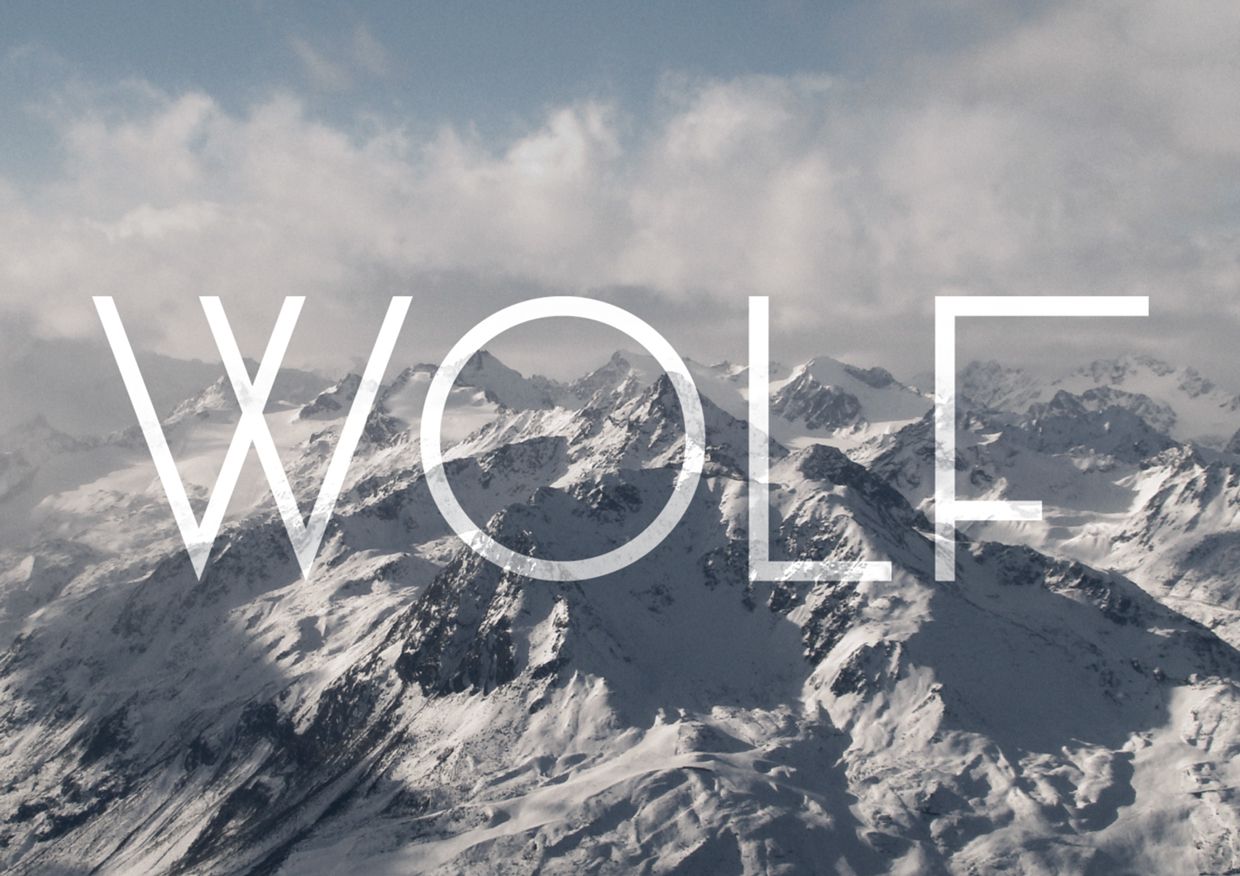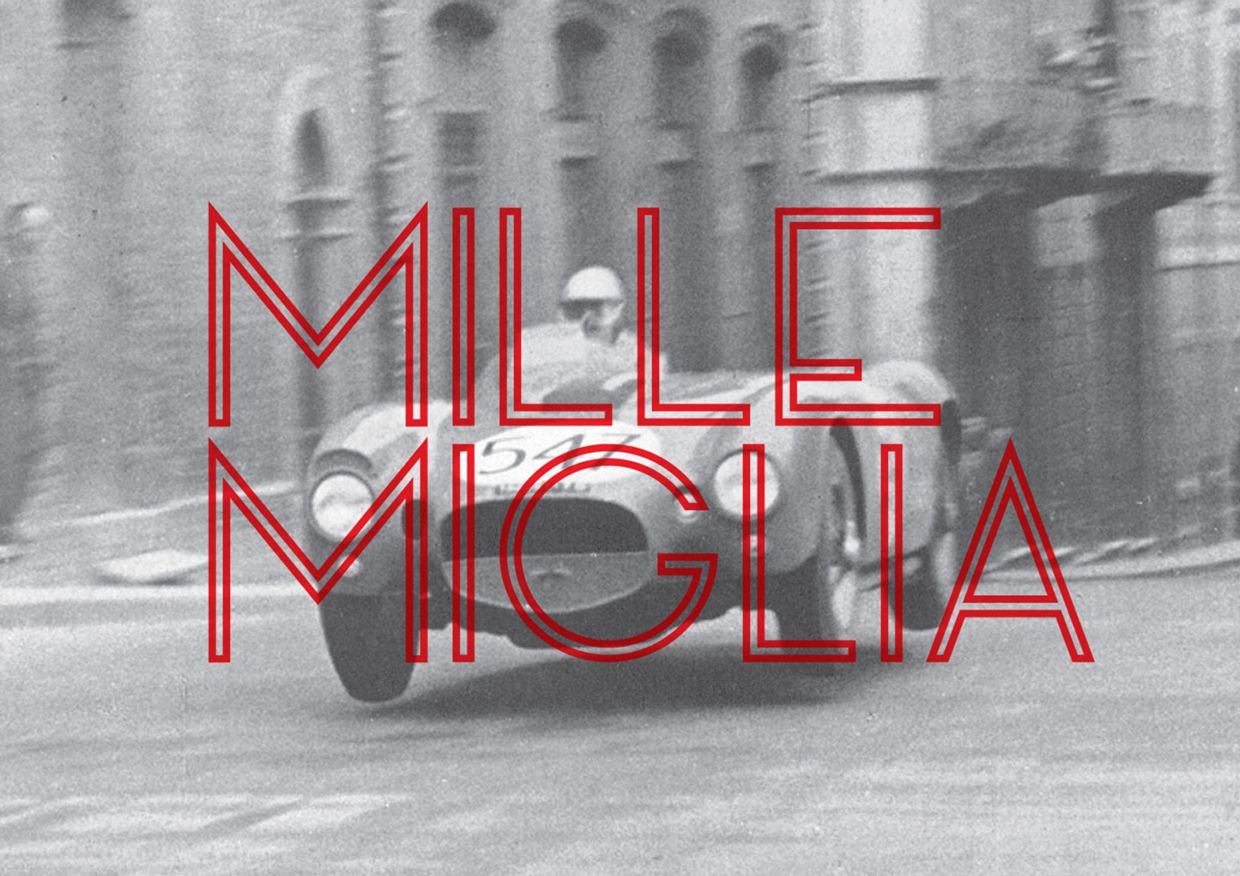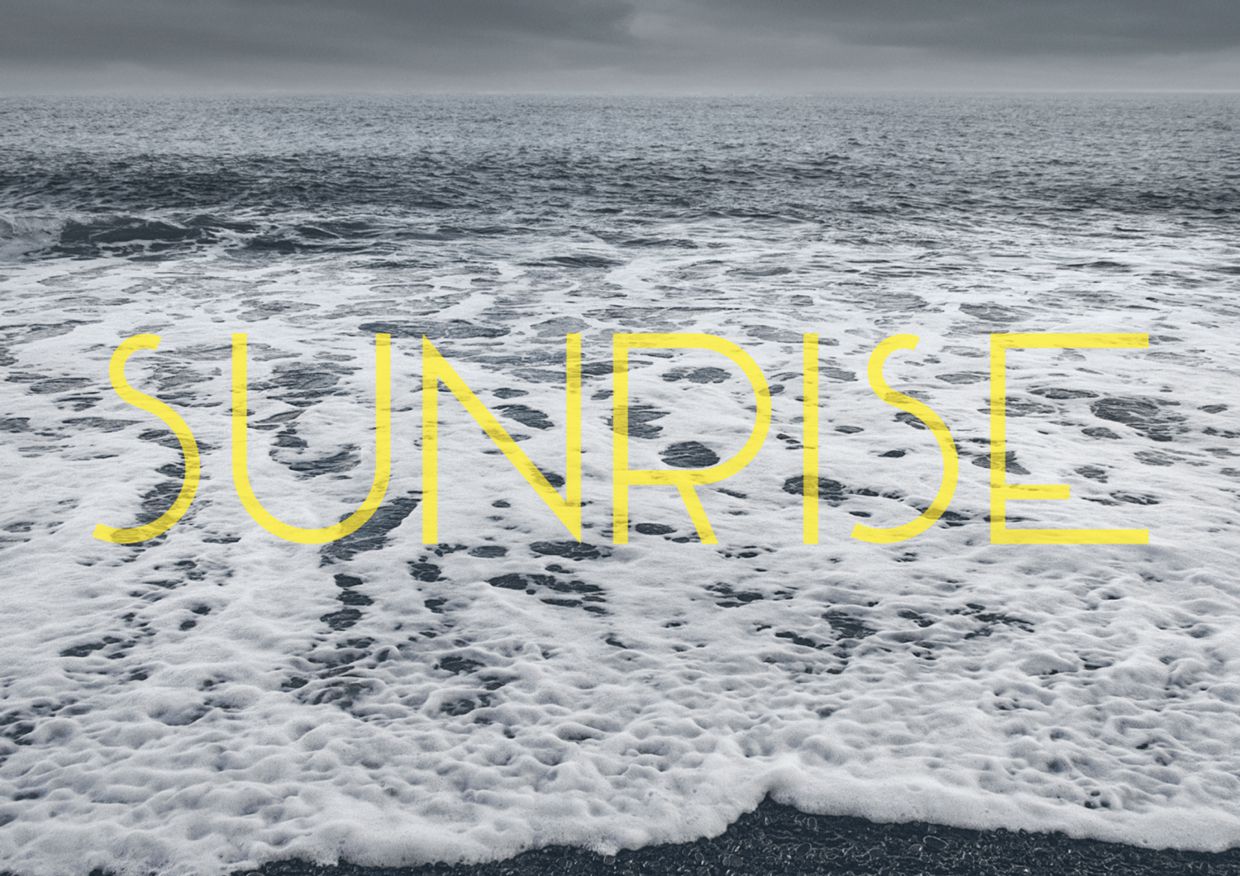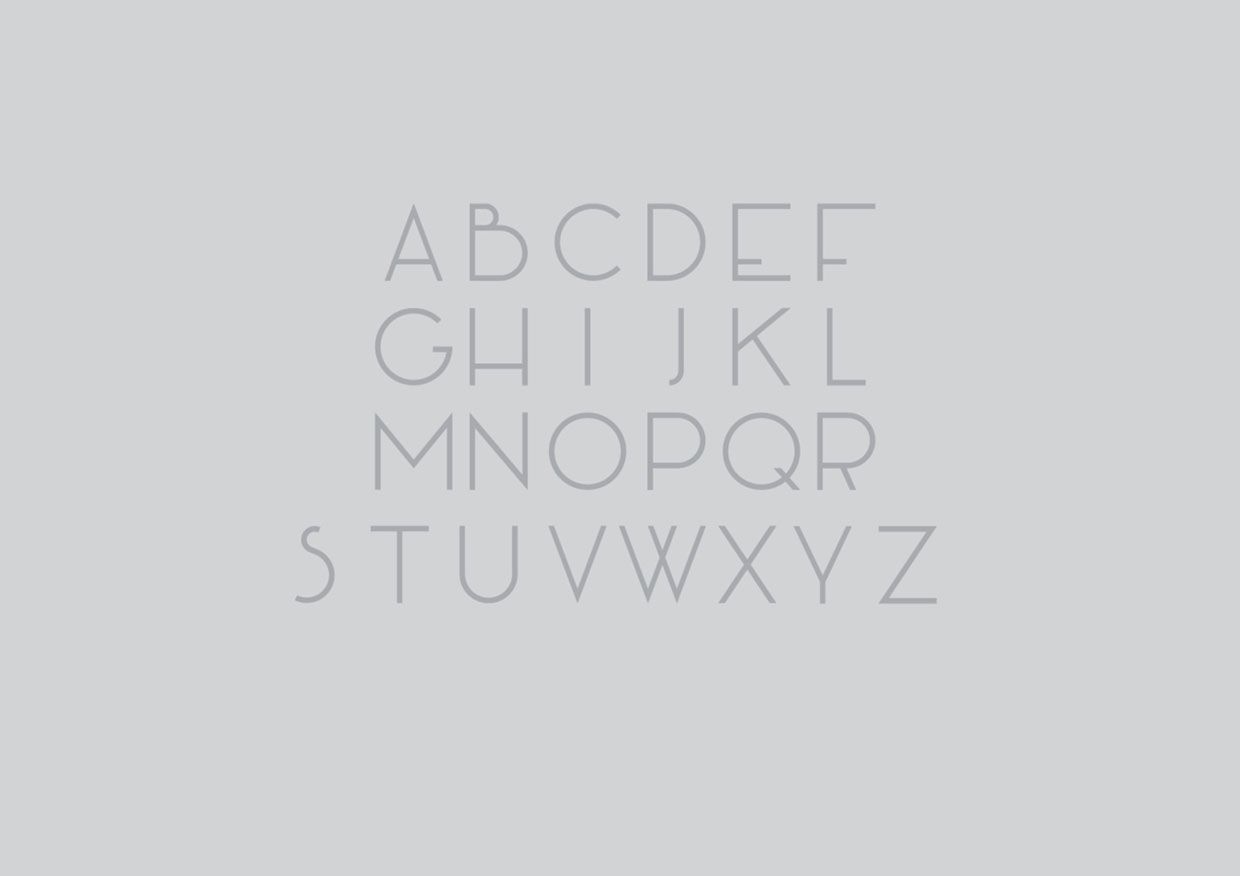
Un lunes más estamos de vuelta con nuestro especial dedicado a las fuentes tipográficas gratuitas para descargar. Hoy damos paso a Manifesto, una tipo sans serif inspirada en el movimiento racionalista italiano de los años 20 y 30. Gracias al diseñador gráfico esloveno Tomaz Leskovec por este aporte gratuito a la comunidad.